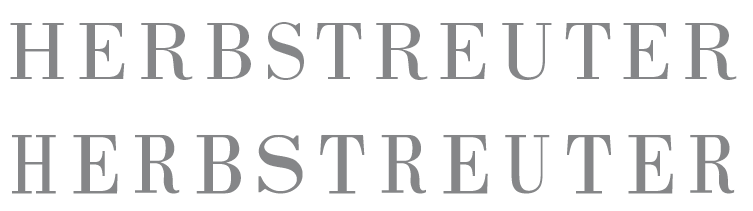
Fragen zur Typographie
zunächst einmal möchte ich sagen, dass ich ein absoluter Newbe bin in Sachen Design, Typographie, Farbgebung und und und....
Ich wollte ein Logo erstellen und habe Fragen zur Eignung des Schrifttyps und wegen der Laufweite des Wortes im Logo.
Ich wollte dazu wissen, wie ich die Buchstabenbreite richtig einstelle, nach was ich dabei gehen muss.
Das was ich hier poste, wurde mit der Schrift "Bodoni MT" erstellt.
Zu deinem Entwurf: Die Wortmarke in Bodoni spricht mich grundsätzlich an. Sehr seriös, vermittelt Sachlichkeit, Fackkenntnis, Präzision. Das kleine Logo dazu wirkt mir aber zu verspielt: Im Kopf funktioniert die Brücke vom Buchstaben (hat das T eigentlich eine tiefere Bedeutung oder hat das nur grad zufällig eine ikonisch verwertbare Form?) zur Justitia-Waage, aber: da fehlt mir irgendwie der souveräne Ausdruck, ein bisschen naiv-verspielt eben; und obendrein seh ich da ein Gesicht mit schamvoll geschlossenen Augen ...
Nochmals zu dem Schriftzug "H e r b s t r e u t e r":
Habe die einzelnen Buchstaben in Illustrator angeglichen, Abstand, Breite der jeweiligen Buchstaben, gleiche Buchstabenhöhe.
Habe die Buchstaben in Kurven umgewandelt und dann milimetergenau
angeglichen. Bin ich da falsch vorgegangen?
Gibst es irgendwo etwas zum nachlesen, wie man die Buchstaben richtig korrigiert und auf was es darauf ankommt?
… Habe die einzelnen Buchstaben in Illustrator angeglichen, Abstand, Breite der jeweiligen Buchstaben, gleiche Buchstabenhöhe. Habe die Buchstaben in Kurven umgewandelt und dann milimetergenau angeglichen. Bin ich da falsch vorgegangen? … tschio
Bei einer "guten" Schrift sind die Buchstaben eigentlich schon so perfekt gezeichnet, dass jede Angleichung eine Verschlechterung ist. Buchstabenhöhe und -breite sind ja normalerweise nach optischen Gesichtspunkten entstanden, nicht nach metrischen. Wie du an deinem Beispiel erkennen kannst ist z.B. das S zu dominant und sieht aus, als wäre es einem Extended-Schnitt entsprungen, das U ist zu schmal geraten …
Probier doch einfach mal aus, ob es nicht besser kommt wenn du die Schrift unangetastet lässt und nur die Spationierung änderst …
Zum Vergleich:
oben: einfach aus der unveränderten Bodoni gesetzt und spationiert
unten: deine Vorlage
Habe die einzelnen Buchstaben in Illustrator angeglichen, Abstand, Breite der jeweiligen Buchstaben, gleiche Buchstabenhöhe.
Ich halt ein solch machanistisches Vorgehen nicht für die Methode der Wahl: Der Schriftgestalter hat unglaublich Brain in die Gestaltung der einzelnen Buchstaben gesteckt, der ist der Fachmann für die Gestaltung der Buchstaben, da sollte man mit einer gewissen Demaut davor stehen und nicht hoppla-hopp hier was ziehen und da was stauchen. Im Ergebnis kommen bei deiner Wortmarke das H und das U zu schmal, das S ist dagegen eindeutig zu voluminös.
Belass es doch bei einem feinfühligen Ausgleich der Buchstabenabstände; leg dabei das Lineal weg und lass dich von deinem Auge leiten ...
Doppelt hält besser :gimmifive:
Wie schon gesagt wurde: bei Schriften wie der Bodoni gibt es an den Buchstaben selbst eigentlich nichts zu korrigieren, auch wenn sie - dem Millimetermaß nach - nicht gleich breit sind, so sind sie doch optisch aufeinander abgestimmt.
Wenn du einen Schriftzug nur in Großbuchstaben schreibst, solltest du aber die generelle Laufweite (also die Buchstabenabstände) erweitern (was du auch getan hast). Die Großbuchstaben in gewöhnlichen Schriften sind darauf ausgelegt, zusammen mit den Kleinbuchstaben zu funktionieren. D.h. der Abstand danach (die Nachbreite) ist relativ gering - für reine Großbuchstaben-Schreibweise zu gering. Also generell etwas Laufweite dazugeben.
Wirf mal einen Blick in die Palette "Zeichen" (Fenster – Schrift – Zeichen).
BS ist noch ein bisschen gar eng aneinander... Mach da noch ein
bisschen was Raum rein.
Warum willst Du jetzt Schriften in Pfade umwandeln???